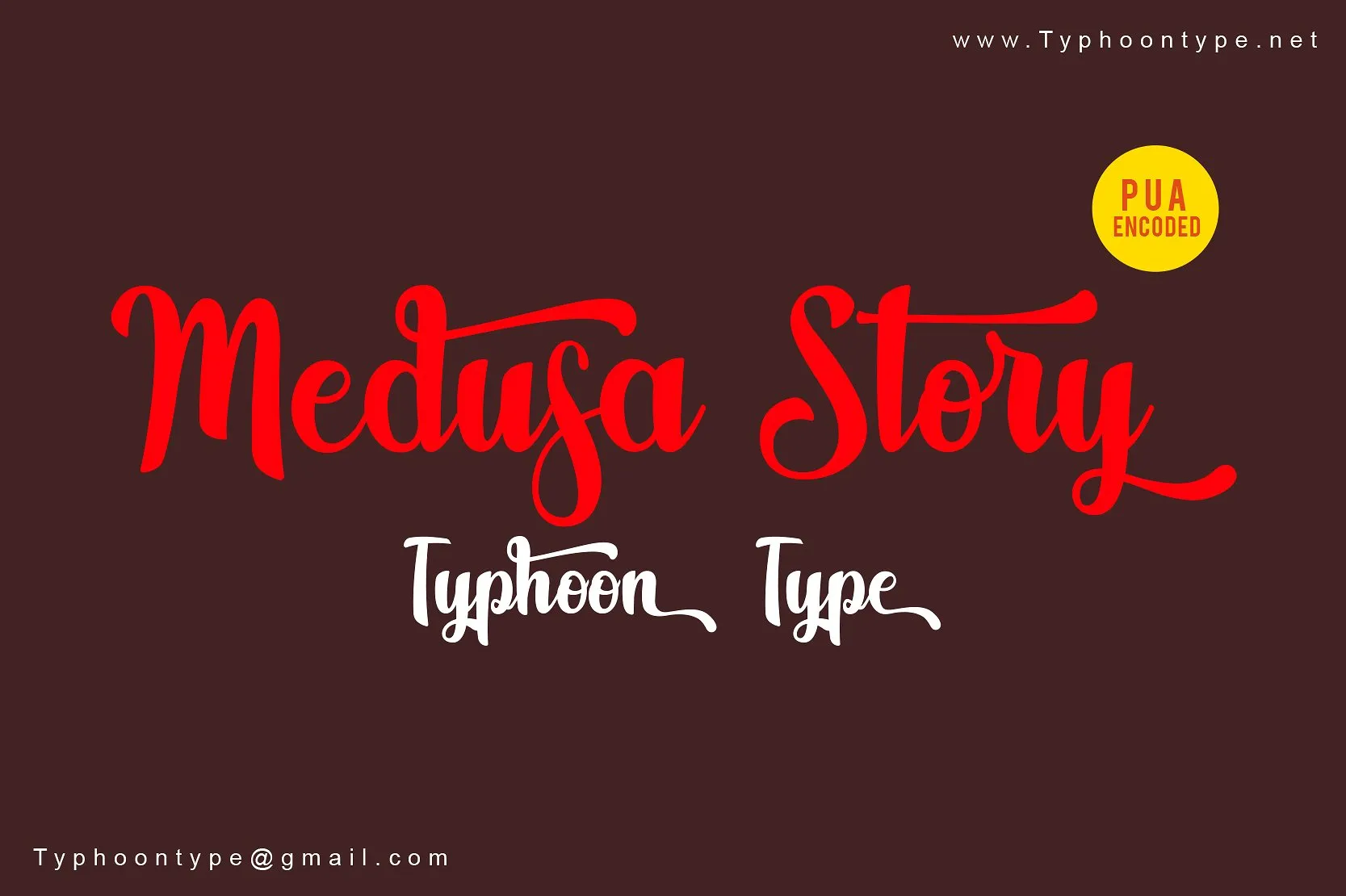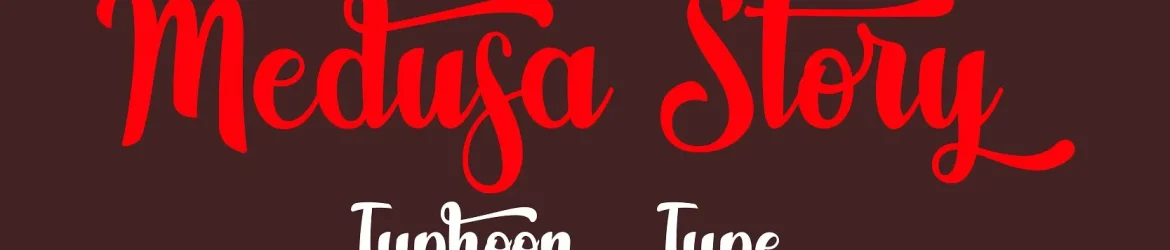
Medusa Story Script Font – Download Grátis
Introduzimos a Medusa Story Font! Esta é uma nova opção fresca e moderna no gênero script, com um estilo de escritura manual. Medusa Story está perfeitamente equipada para uso em logotipos, tags de nome, anúncios, embalagens de produto, roupas, mídia social e cartões de agradecimento. Seja você designer de gráficos ou criador de produtos, este é um recurso valioso que oferece uma variedade de opções para personalizar seus projetos. Medusa Story é perfeito para aqueles que desejam dar um toque único à sua identidade visual e aos elementos digitais dos quais são parte. Essa fonte é especialmente indicada para criações modernas, combinando elegância com uma sensação de originalidade genuína através do seu estilo handmade. É a escolha ideal para quem busca criar algo que se destaque nos seus materiais em linha e offline, seja em cartazes urbanos, peças digitais ou impressões no papel. Combinada com outros elementos gráficos, você pode usar Medusa Story Font para dar vida aos seus projetos de design. Estamos certos de que esta fonte moderna irá tornar suas criações ainda mais únicas e atraentes. Descubra como essa font poderosa faz parte da sua paleta de recursos criativos!